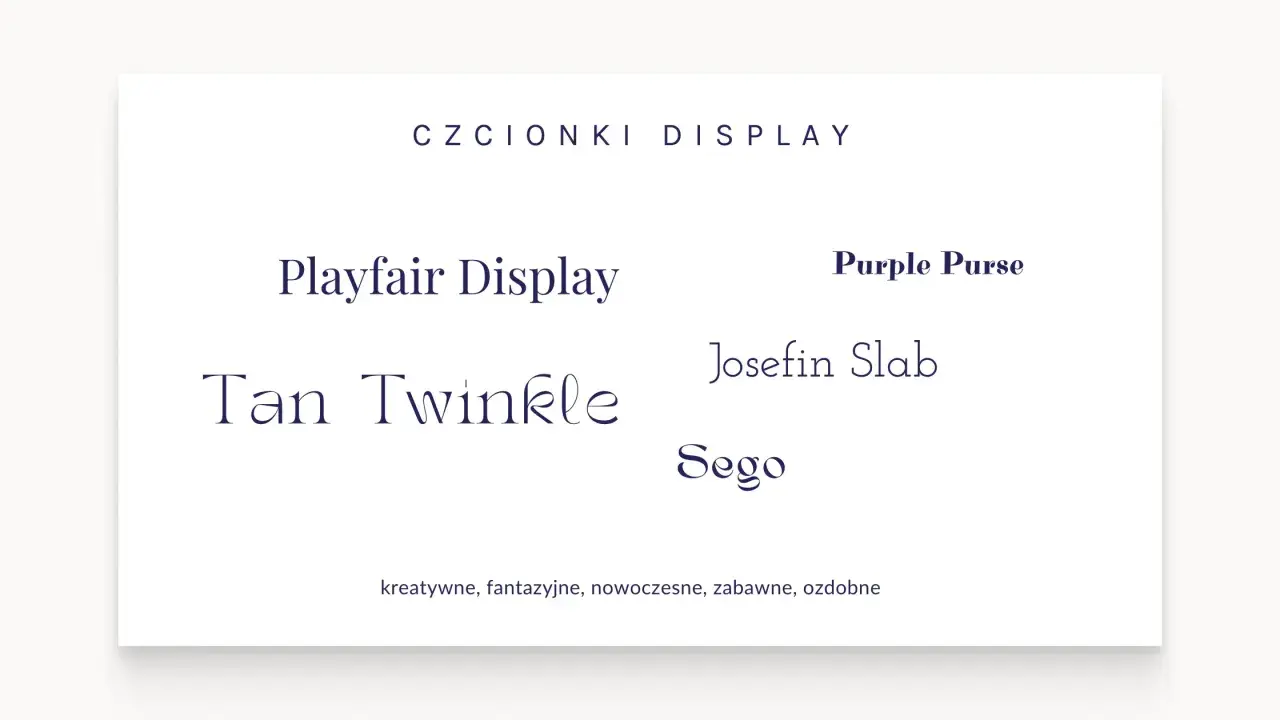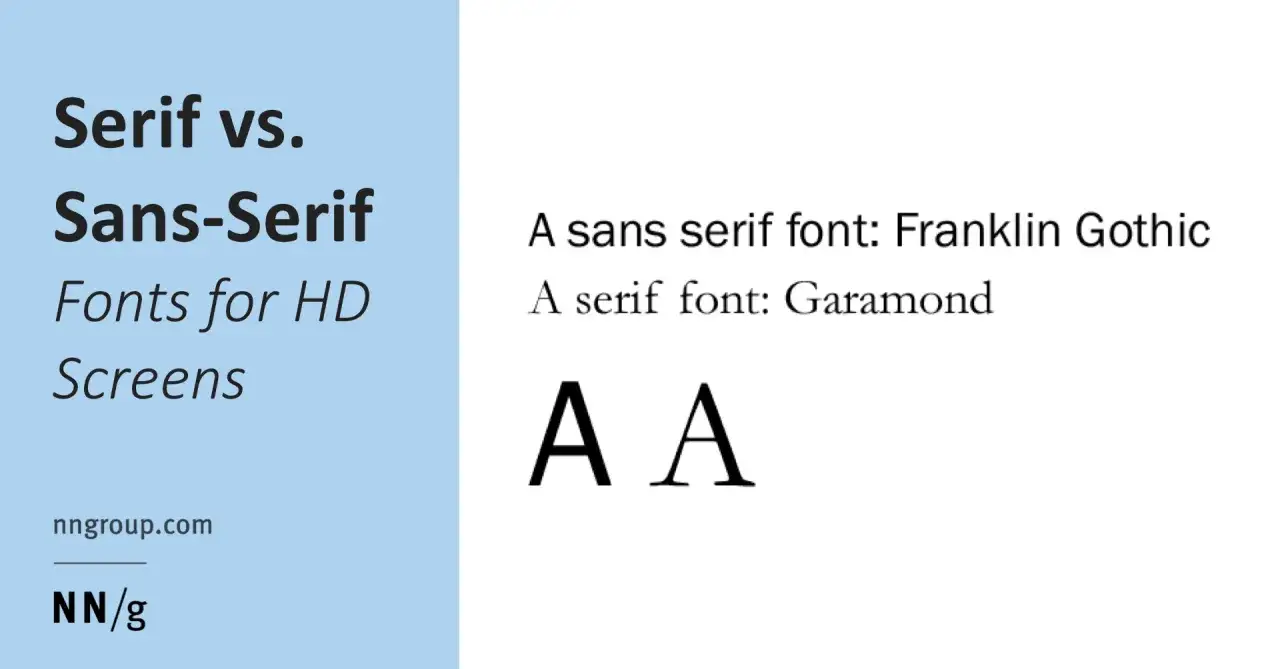
Podstawowe czcionki – wybierz idealny krój dla Twojej strony
Przykłady czcionek display: Playfair Display, Tan Twinkle, Purple Purse, Josefin Slab, Sego. Kreatywne, fantazyjne, nowoczesne, zabawne, ozdobne.
Wybór kroju pisma wpływa na to, czy tekst daje się czytać bez wysiłku, jak odbierana jest marka i czy strona wygląda spójnie na różnych urządzeniach. Ten tekst porządkuje podstawowe czcionki, pokazuje najczęściej używane rodziny oraz tłumaczy, kiedy warto zostać przy klasyce, a kiedy sięgnąć po font bardziej charakterystyczny. Skupiam się na rozwiązaniach praktycznych dla stron internetowych, sklepów i treści, które mają być po prostu wygodne w odbiorze.
Najkrótsza droga do dobrego wyboru kroju
• Najczęściej pracuje się na trzech rodzinach: szeryfowej, bezszeryfowej i monospace.
• Na stronach internetowych liczy się nie tylko wygląd, ale też szybkość ładowania i czytelność na małym ekranie.
• Jedna rodzina bazowa, jeden sensowny fallback i ograniczona liczba wag zwykle dają lepszy efekt niż kilka przypadkowych fontów.
• Do długich treści najlepiej wybierać kroje spokojne, z dobrym rozróżnieniem liter i solidnym wsparciem polskich znaków.
• Font dekoracyjny ma sens w nagłówku lub brandingu, ale rzadko sprawdza się w akapitach.
Co naprawdę oznaczają podstawowe kroje pisma
W codziennym języku „czcionka” oznacza po prostu font, ale w typografii warto rozróżnić krój pisma od pojedynczej odmiany. Dla czytelnika nie ma znaczenia akademicka definicja, tylko to, czy tekst jest wygodny, spójny i nie męczy wzroku po kilku akapitach.
W praktyce dzielę je na kilka prostych grup, bo to ułatwia decyzję już na starcie. Każda z nich rozwiązuje inny problem i ma własne ograniczenia.
Rodzina Jak się zachowuje Gdzie ma sens Przykłady
Szeryfowe Bardziej klasyczne, redakcyjne, „osadzone” w tekście Dłuższe artykuły, treści premium, materiały formalne Georgia, Times New Roman, Garamond
Bezszeryfowe Czyste, neutralne, zwykle najbardziej uniwersalne na ekranie Strony www, interfejsy, e-commerce, komunikaty Arial, Helvetica, Verdana, Tahoma, Roboto
Monospace Każdy znak zajmuje podobną szerokość Kod, logi, dane techniczne, fragmenty techniczne w treści Courier New, Consolas, Monaco
Systemowe Korzystają z fontu dostępnego na urządzeniu użytkownika Interfejsy, aplikacje webowe, projekty, w których liczy się szybkość system-ui, Segoe UI, San Francisco, Roboto
Webfonty Ładowane z pliku lub usługi zewnętrznej, dają większą kontrolę nad stylem Branding, landing page, serwisy, w których typografia jest elementem identyfikacji Inter, Open Sans, Lato
Ten podział wystarcza, żeby odsiać większość pomysłów, które wyglądają efektownie na makiecie, ale słabiej działają w realnym użyciu. Kiedy wiem, z której grupy wybieram, łatwiej przejść do konkretnych fontów i ich ról.
Porównanie podstawowe czcionki bezszeryfowej (Franklin Gothic) i szeryfowej (Garamond) na ekranach HD.
Najczęściej używane fonty i ich typowe role
Jeśli miałbym zbudować stronę bez kombinowania, sięgnąłbym właśnie po te kroje. Nie dlatego, że są modne, tylko dlatego, że są przewidywalne, dobrze czytelne i łatwo dopasować do nich resztę interfejsu.
Font Co daje Najlepsze zastosowanie Na co uważać
Arial / Helvetica Neutralność i prostotę UI, formularze, proste strony firmowe Potrafią wyglądać zbyt „bezpiecznie”, jeśli marka chce mocniejszego charakteru
Verdana Świetną czytelność na ekranie Dłuższe bloki tekstu, małe rozmiary, treści informacyjne Jest dość szeroka, więc zajmuje sporo miejsca
Tahoma Dobry balans między kompaktowością a czytelnością Menu, panele, gęstsze interfejsy W dużych akapitach bywa mniej „oddychająca” niż Verdana
Georgia Elegancję i spokojny rytm czytania Blogi, artykuły, treści redakcyjne, marki premium Na bardzo małych ekranach wymaga rozsądnego rozmiaru i interlinii
Times New Roman Formalny, klasyczny wygląd Dokumenty, treści oficjalne, teksty wymagające neutralności Na stronie internetowej często wygląda zbyt szkolnie lub archaicznie
Trebuchet MS Trochę więcej charakteru bez utraty czytelności Nagłówki, marketing, strony usługowe Nie zawsze pasuje do bardzo poważnego, korporacyjnego tonu
Courier New / Consolas Monospace i techniczny porządek Kod, specyfikacje, fragmenty logów, dane liczbowe Nie nadają się do długich akapitów
Roboto / Open Sans / Inter Nowoczesny, internetowy wygląd Strony, aplikacje, sklepy, systemy SaaS To zwykle webfonty, więc trzeba liczyć się z ładowaniem plików
W polskich projektach zawsze sprawdzam też diakrytyki, bo font może wyglądać świetnie na angielskim demo, a rozsypać się przy „ą”, „ę”, „ł” albo „ż”. To drobiazg, który od razu odróżnia dobry wybór od przypadkowego.
Jak dobrać krój do strony, sklepu i treści redakcyjnej
Nie wybieram fontu od mody, tylko od zadania. Inny krój sprawdzi się w sklepie internetowym, inny w długim artykule, a jeszcze inny w aplikacji, gdzie liczy się tempo i brak tarcia poznawczego.